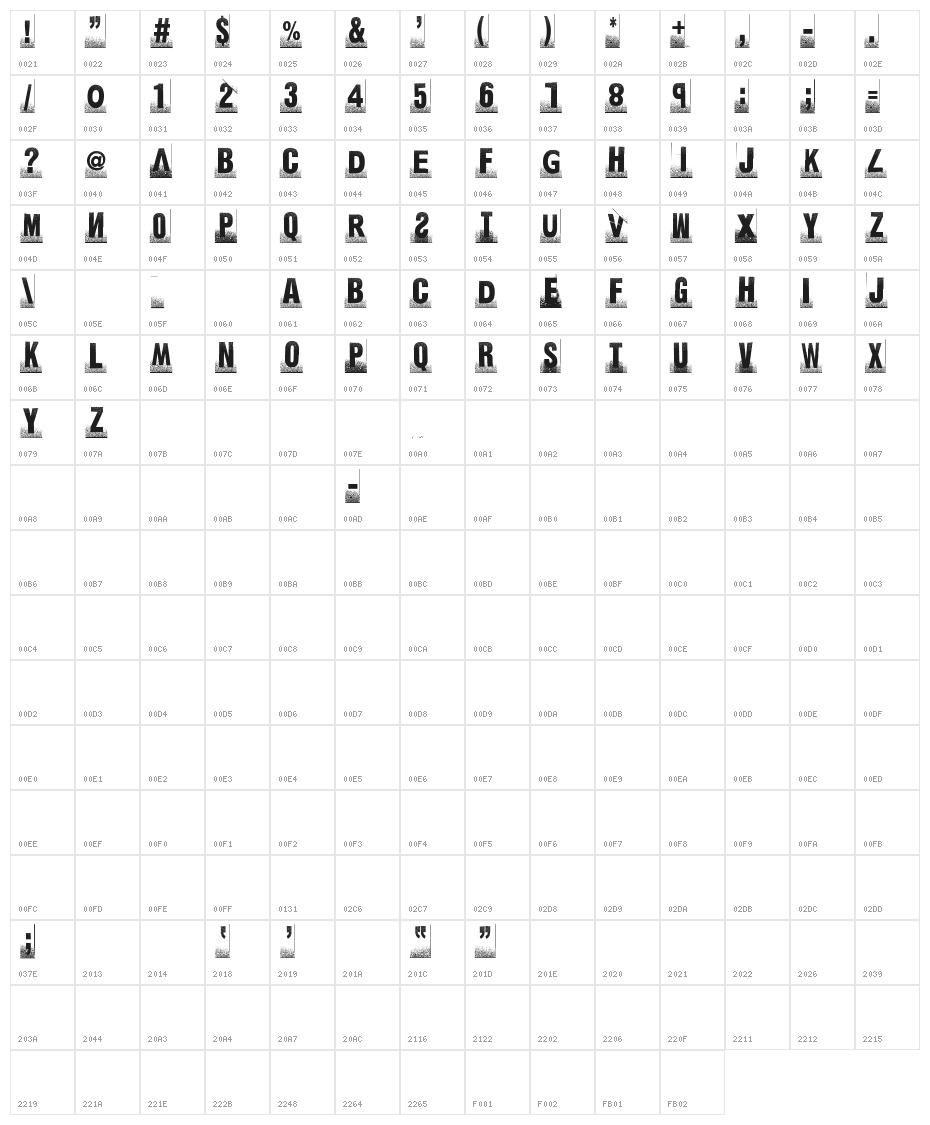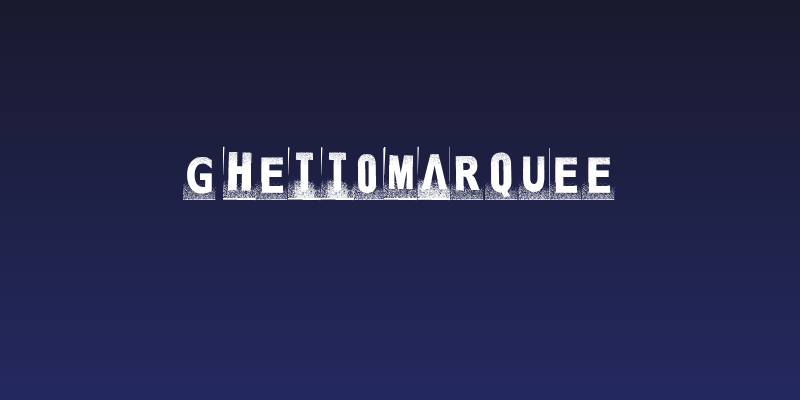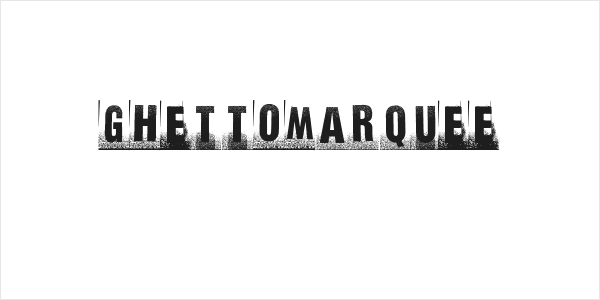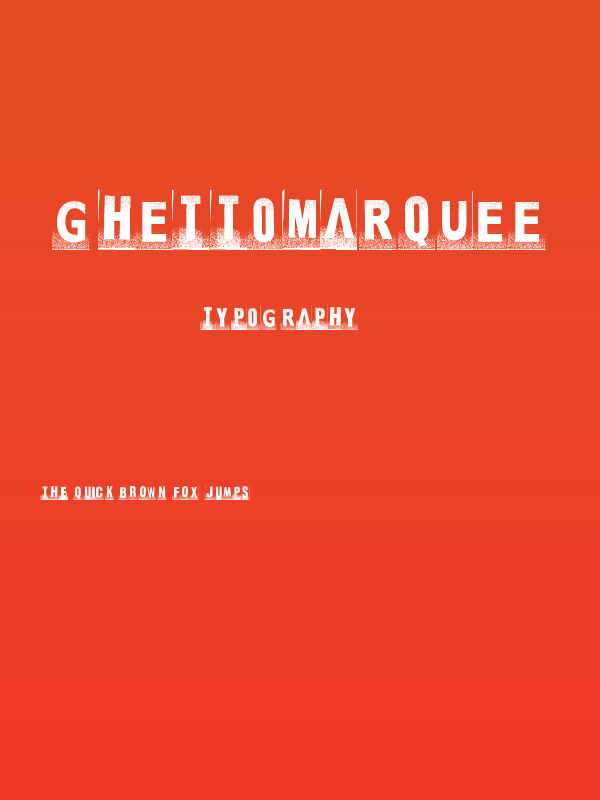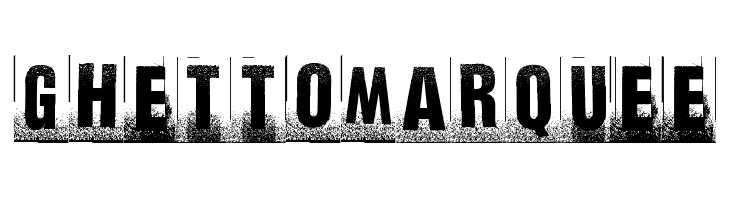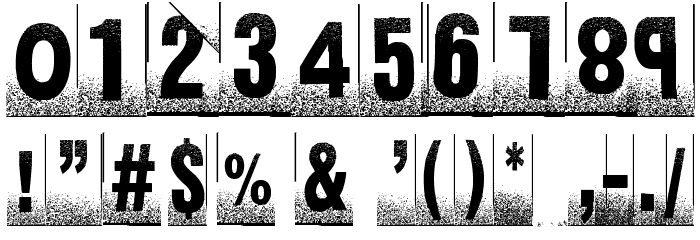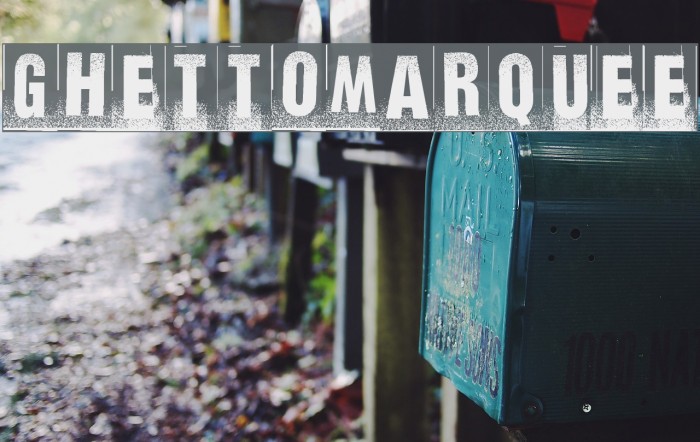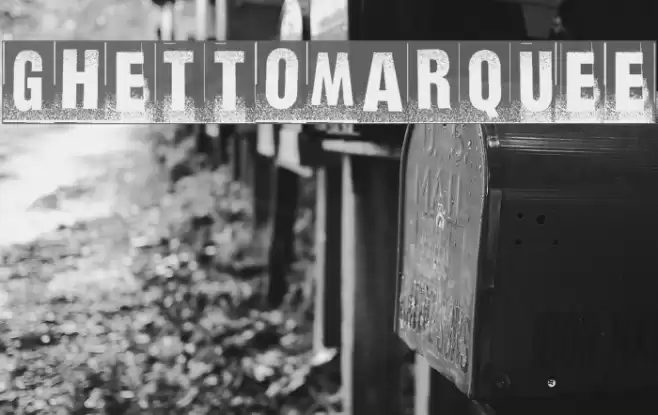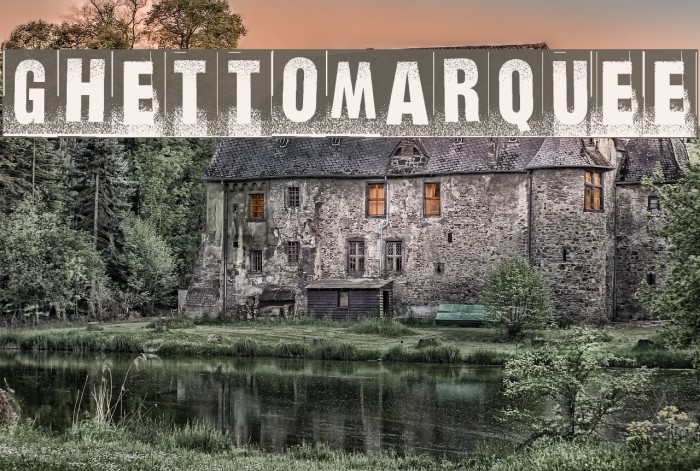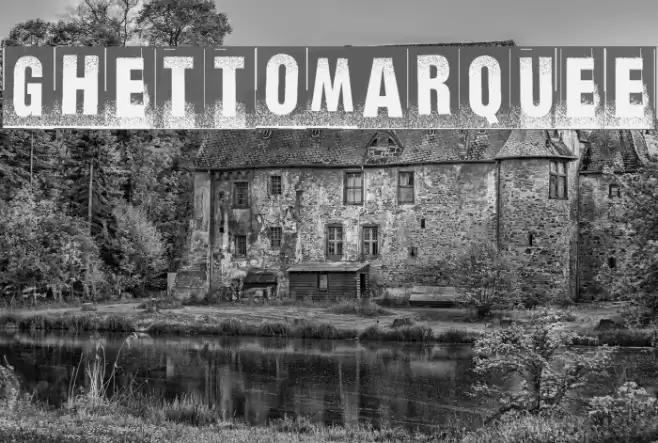
ghettomarquee Font
✎ Graffiti
| Categorii | Graffiti |
| Stil general | Urban, Edgy, Distressed |
| Proiecte propuse | Ideal for urban-themed designs, posters, album covers, streetwear branding, and event flyers. |